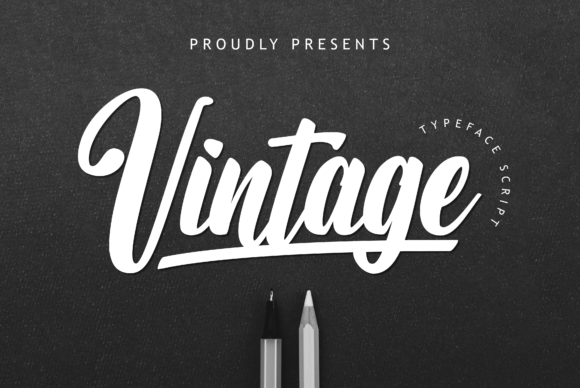
Vintage
Vintage – La police cursive qui sublime vos créations
Vous cherchez une typographie à la fois chic, professionnelle et pleine de caractère ? Vintage est la réponse. Conçue avec une grande minutie, cette police script élégante apporte une touche d’élégance sophistiquée à chaque projet. Que vous travailliez sur des titres percutants, des logos mémorables, du design d’objets artisanaux ou des collections de merchandising, Vintage transforme votre mise en page en une véritable œuvre d’art.
Pourquoi choisir Vintage ?
- Design soigné et lisible – Chaque glyphe est tracé avec précision, garantissant une lecture fluide même en petites tailles.
- Style cursif raffiné – Le caractère manuscrit apporte chaleur et authenticité, idéal pour les marques qui veulent se démarquer.
- Polyvalence – Parfait pour les headlines, les logos, les étiquettes de vêtements, les cartes de visite et tout support de merch.
- Impact visuel – Une typographie qui capte immédiatement l’attention et renforce le message de votre marque.
Utilisations idéales de Vintage
Grâce à son style à la fois moderne et rétro, Vintage s’intègre parfaitement dans les projets suivants :
- Logotypes d’entreprises de mode et de lifestyle.
- Affiches d’événements, festivals et soirées à thème vintage.
- Emballages de produits artisanaux (cosmétiques, bougies, bijoux).
- Impressions sur t‑shirts, casquettes, tote‑bags et autres produits dérivés.
- Cartes d’invitation, faire‑part et papeterie de mariage.
En résumé, Vintage n’est pas seulement une police : c’est un atout stratégique qui donne du poids à votre identité visuelle tout en captivant votre audience. Adoptez‑la dès maintenant et constatez la différence !